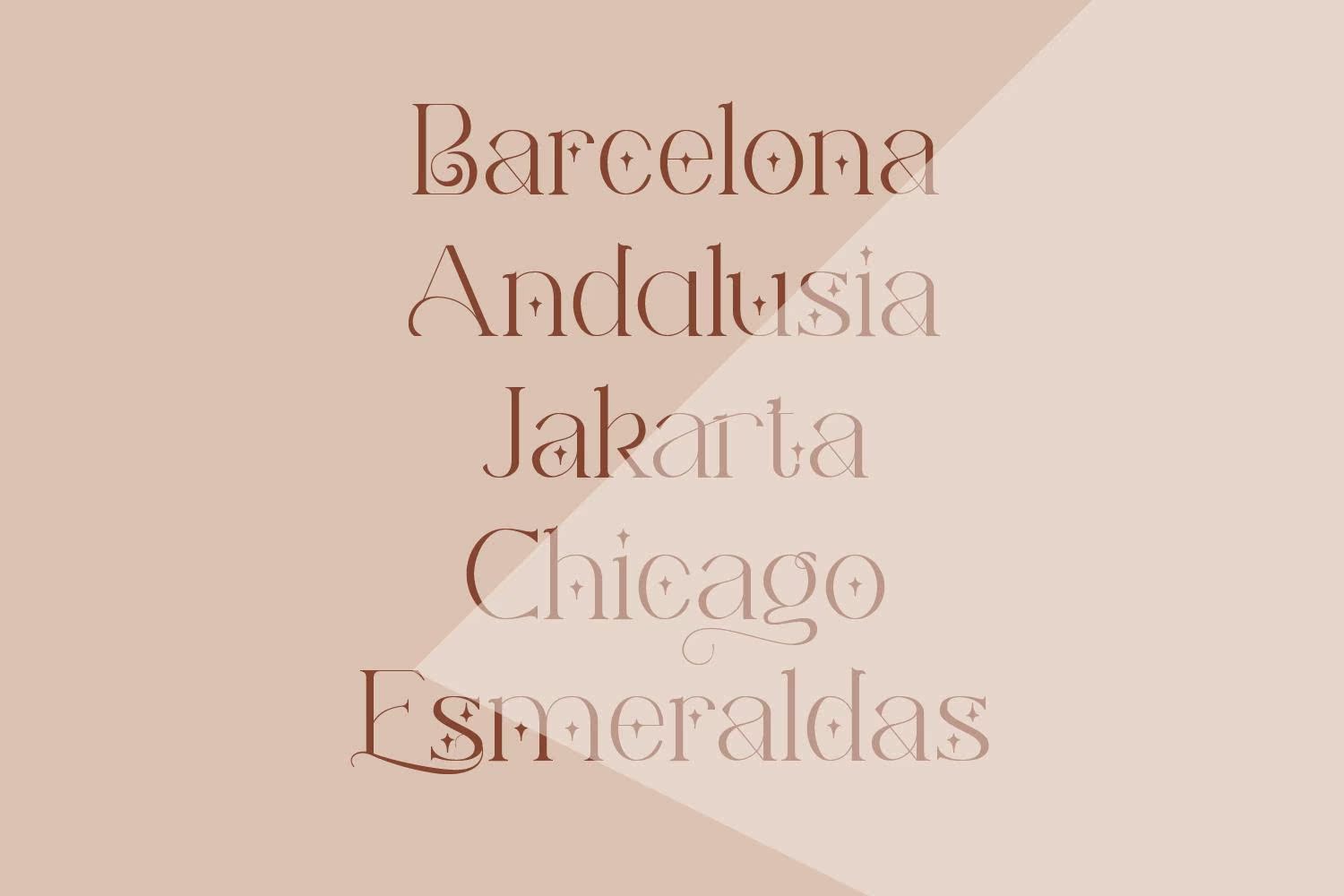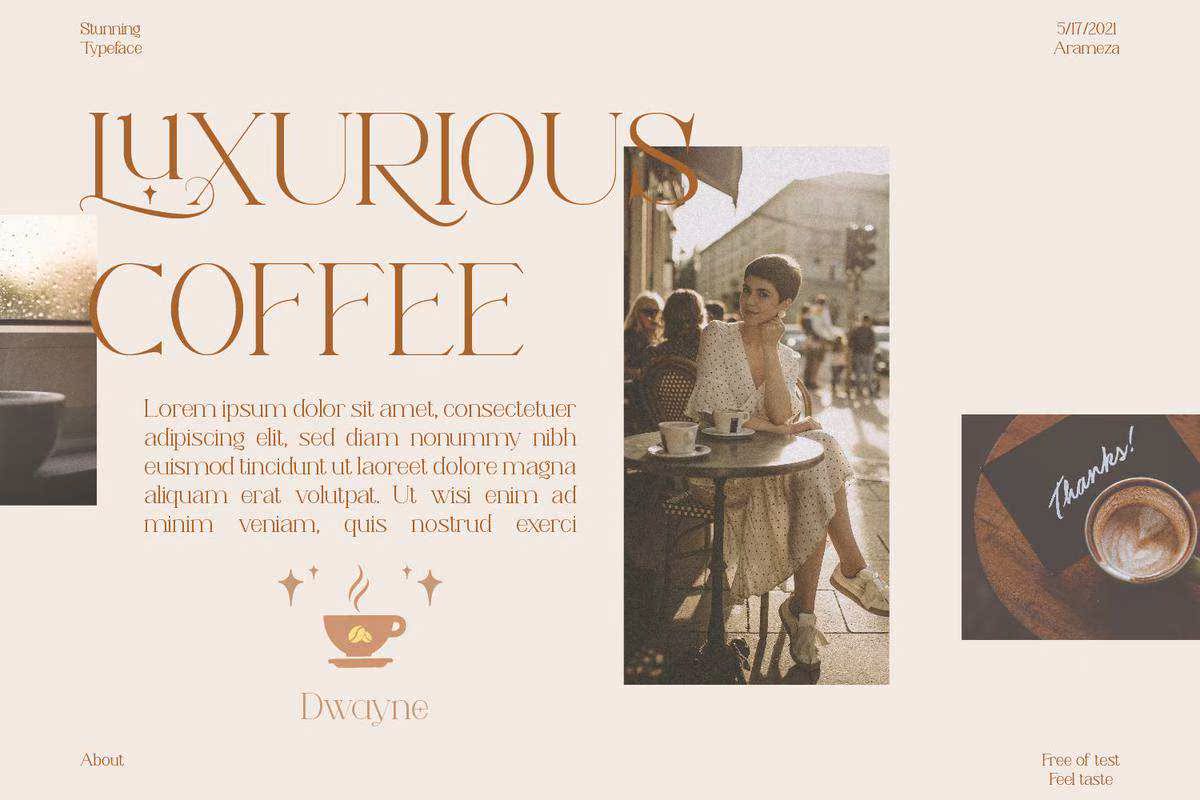
简介:Garameza,Astuningserifont.Aramezacomes,具有简洁、奢华和华丽的字体风格。该字体非常适合各种设计目的。不要为了给每个角色留下丰富的印象,它在每个设计项目中都具有附加价值,如后期设计、邀请牌、网络写作、横幅设计、包装、品牌,该字体支持名片和许多其他设计项目。该字体还支持多种语言。介绍Garameza,AstuningsPerifent。Aramezacomes,具有简洁、奢华和华丽的字体风格。该字体非常适合各种设计目的。不要给每个角色留下过多的印象,它为每个设计项目提供了附加价值,例如PosterDesign、邀请函、网络写作、横幅设计、包装、品牌、名片和许多其他设计项目都可以使用此字体支持。此字体还支持多种语言。